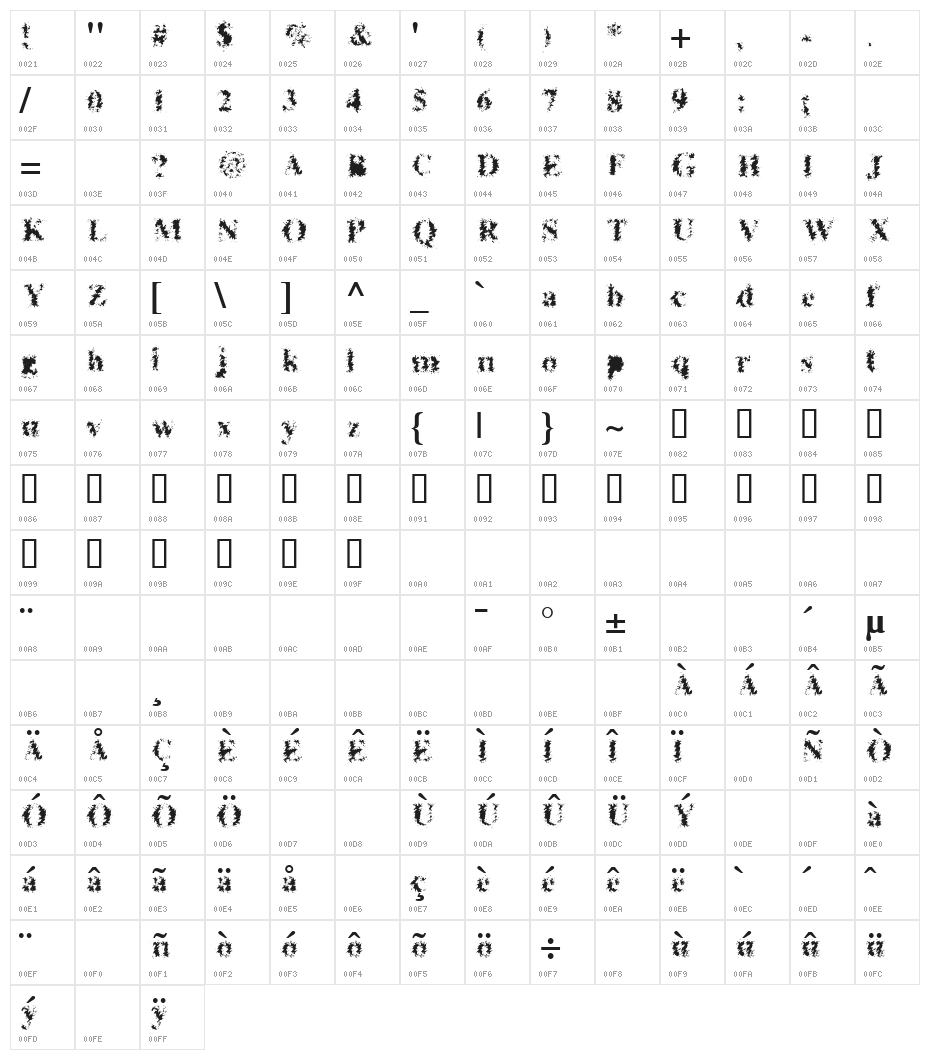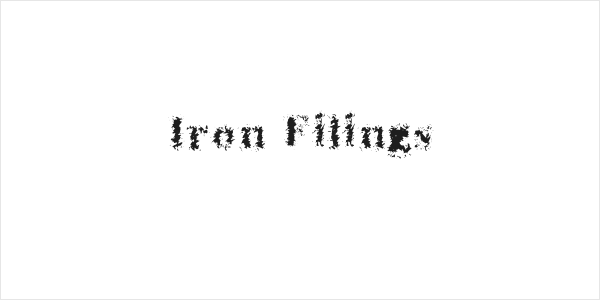
Iron Filings Font
| Gesamtstil | Industrial, Edgy |
| Vorgeschlagene Projekte | Ideal for album covers, posters, branding for industrial-themed products, or any design needing a bold, gritty look. |